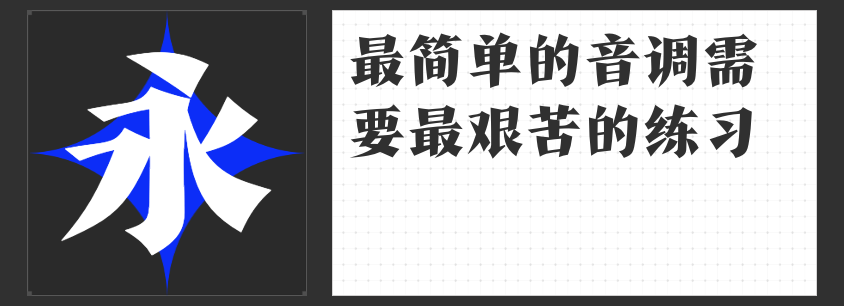
四款招牌字体推荐,为设计注入独特魅力
在商业设计中,招牌字体是吸引顾客目光、传递品牌个性的关键元素。今天为大家推荐四款各具特色的招牌字体,它们能为你的设计作品增添别样的风采。
一、造字侠磅礴简繁
造字侠磅礴简繁字体中正,感官丰富,运笔极具节奏感,呈一波三折之态。笔画粗细变化明显,略带飞白,转折处方圆结合,刚柔并济。这种字体犹如一位沉稳的将军,既有磅礴的气势,又不失细腻的情感。适用于大型商场、文化场馆等场所的招牌设计,能够彰显出品牌的雄厚实力与深厚底蕴,给人以大气、庄重之感。
二、造字侠醉春风简繁 苍劲
造字侠醉春风简繁 苍劲整体风格自由率真、活泼灵动。单字结构周正却不失松弛,点画圆润,笔画间粗细过渡自然,灵动的笔画走势造就了独特的字形风貌。它就像一阵春风,带着生机与活力,吹进人们的视野。适合用于餐饮、娱乐等行业的招牌,能营造出轻松愉悦的氛围,吸引顾客驻足。
三、造字侠侠道简繁
造字侠侠道简繁字形饱满,松弛自然,回锋收笔,转折处笔画突出,有适度的夸张和飞白,给人一种立于天地间的桀骜不驯之感。整体布白均匀,风格独特,节奏鲜明。这种字体适合潮流品牌、创意工作室等场所的招牌,能够展现出品牌的个性与态度,让人过目难忘。
四、高手字斋东京体
高手字斋东京体粗体敦厚疏朗,长宽相等的方块字型利于使用和表达诉求。锋利的笔画十分清晰,无论横排、竖排都能大大提高醒目度,在正常环境中更具“跳出性”,入眼入心。光洁平滑的字体曲线让人感到亲和舒畅,简洁又新颖的造型更容易记忆深刻。适用于各类店铺招牌,尤其是追求时尚、简约风格的场所,能让品牌在众多竞争对手中脱颖而出。
这四款招牌字体,或磅礴大气,或灵动活泼,或桀骜不驯,或清晰亲和,能为你的设计带来无限可能。